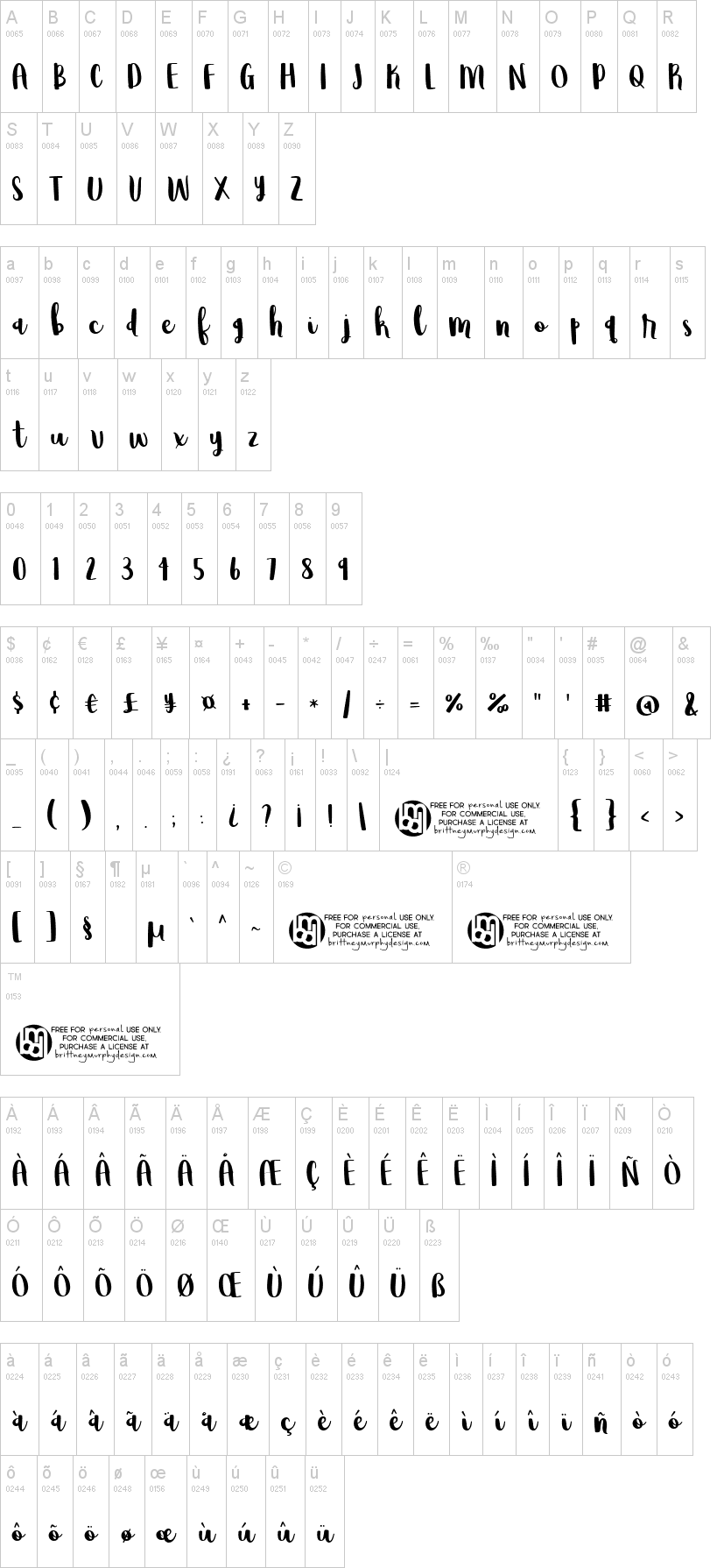
Wildemount
Wildemount是一种流行的手写字体,灵感来自于Dungeons & Dragons游戏中的Wildemount地区。这种字体具有独特的笔画和装饰性,设计师使用了手写和手绘技巧来制作它。 Wildemount字体的特点包括精美的线条和符号,它们可以用来增强文本的视觉效果。这种字体适用于海报、宣传单、标志和其他需要强制视觉效果的设计项目。总的来说,Wildemount字体是一种具有艺术风格的字体,它可以提供给设计师一种独特的视觉元素,使他们的设计作品更加引人注目。
Wildemount是一款非常不错的手写艺术字体,具有很好的视觉感,适合于文化类的宣传设计、商业类品牌的广告和产品包装设计以及个性化文字排版等较多场景。
Wildemount字符映射图